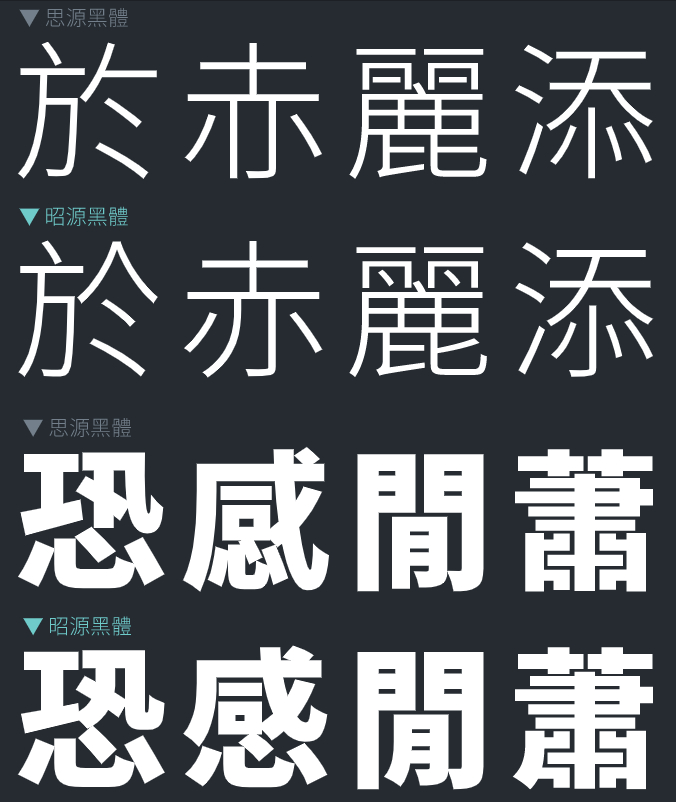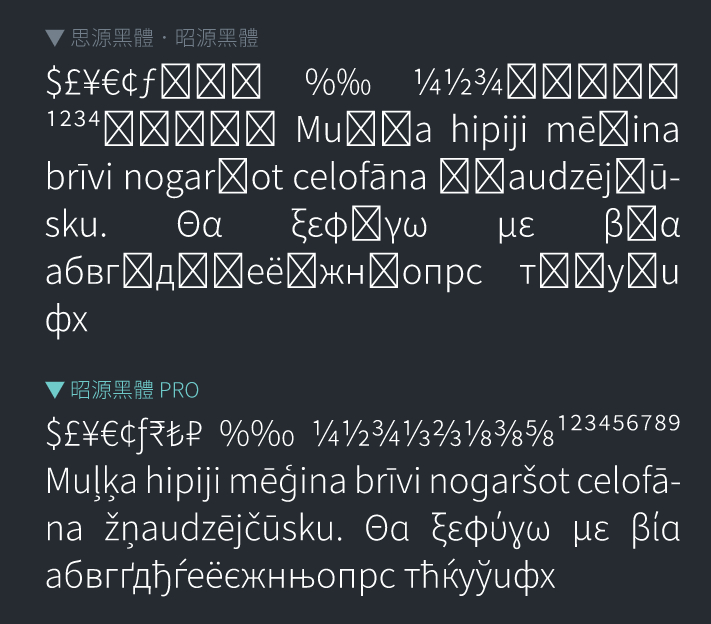
昭源黑体(Chiron Sans HK)以「思源黑体香港版」为基础,参考繁体中文地区的商用字体作出修改,目标是提供一个兼顾标准字形和印刷体架构的开源字体方案。是一款现代笔形风格,平衡标准字形和印刷体惯用笔形的免费开源黑体字型,专为繁体中文用户设计,尤其适用于香港用户。
字重丰富,配搭方:提供丰富字重让使用者自由选择是思源黑体的一大特色。为了提供与思源黑体一致的配搭弹性,昭源黑体所有修改或新造字形都做齐七款字重,现在更备有可变式字型格式。
站在巨人肩膊之上,收字繁多:思源黑体是一款泛中日韩(Pan-CJK) 字体,支援的表意文字字符超过四万,平假片假名、谚文等也一应俱全。昭源黑体除完整保留这些字码支援外,还收有思源黑体没有的新造字。
熟悉 ‧ 亲切:「思源黑体香港版」是依据《香港电脑汉字参考字形》的字形标准设计。《香港电脑汉字参考字形》以手写楷书为本,采取「宋体与楷体字形规律一致的总体原则」,其字形规律「并无楷宋之分」,以维持手写和印刷字形的一致性。在这个原则之下,「参考字形」将好些本来只用于楷书或在以往印刷体(即使是采现代笔形者,无论宋体还是黑体)中极为罕见的部件形态移植到印刷体,其选定的某些笔形或字形结构对一般人来说可能较为陌生,甚至影响辨认。昭源黑体会参考大众日常生活所见的「事实标准」调整字形。
兼顾印刷体效果:属于「手写体」的楷体和属于「印刷体」的宋、黑字体架构不同,过份强调书写笔形会令印刷体失去本来端正、整齐的感觉。「昭源黑体」比较着重显示效果,会按情况选择,不会尽依「参考字形」。
择优而从:有些笔画本来不属「标准差异」,但思源黑体因为各种原因以「地区差异」将写法区分。昭源黑体会尽量选择设计较佳的版本,不拘泥于原来字体对该种笔画的地区划分。
额外增加中文新造字:思源黑体支援的中日韩字集本身已经足够日常使用,几乎不会有缺字问题。昭源黑体除了加入四个香港会用到但不在HKSCS 字集因而未获思源黑体收录的,更额外增加超过1,000 个新造字,使之可以应付以下粤语相关网站的使用(仅限字头)。
针对繁体中文使用场合调整标点:思源黑体香港版的西文单双引号('、'、“、”)以全形显示。由于繁体中文环境多数使用中文款式的单双引号(「」『』),本字体沿用思源黑体日、韩版做法,将西文单双引号改为半形,方便中英混排。另一方面,本字体将以下符号改为预设输出与中文字(而非英文)对齐的版本:U+2E3A(⸺)、U+2E3B(⸻)、U+203C(‼)、U+2047(⁇)、U+2048(⁈)、U+2049(⁉)。由于繁体中文环境不会预设压缩全形标点符号,本字体将相关的halt、vhal、palt、vpal 指令移除,使用排版软件时不须额外设定。
更完整的LGC 收字 (PRO 版):昭源黑体Pro 版继承昭源黑体的所有特点,并进一步整合Source Sans 3 字体,减低使用单套字型时遇到缺字「豆腐」的机会。保留Source Sans 3 的OpenType 功能,提供更丰富的字元变化选择。